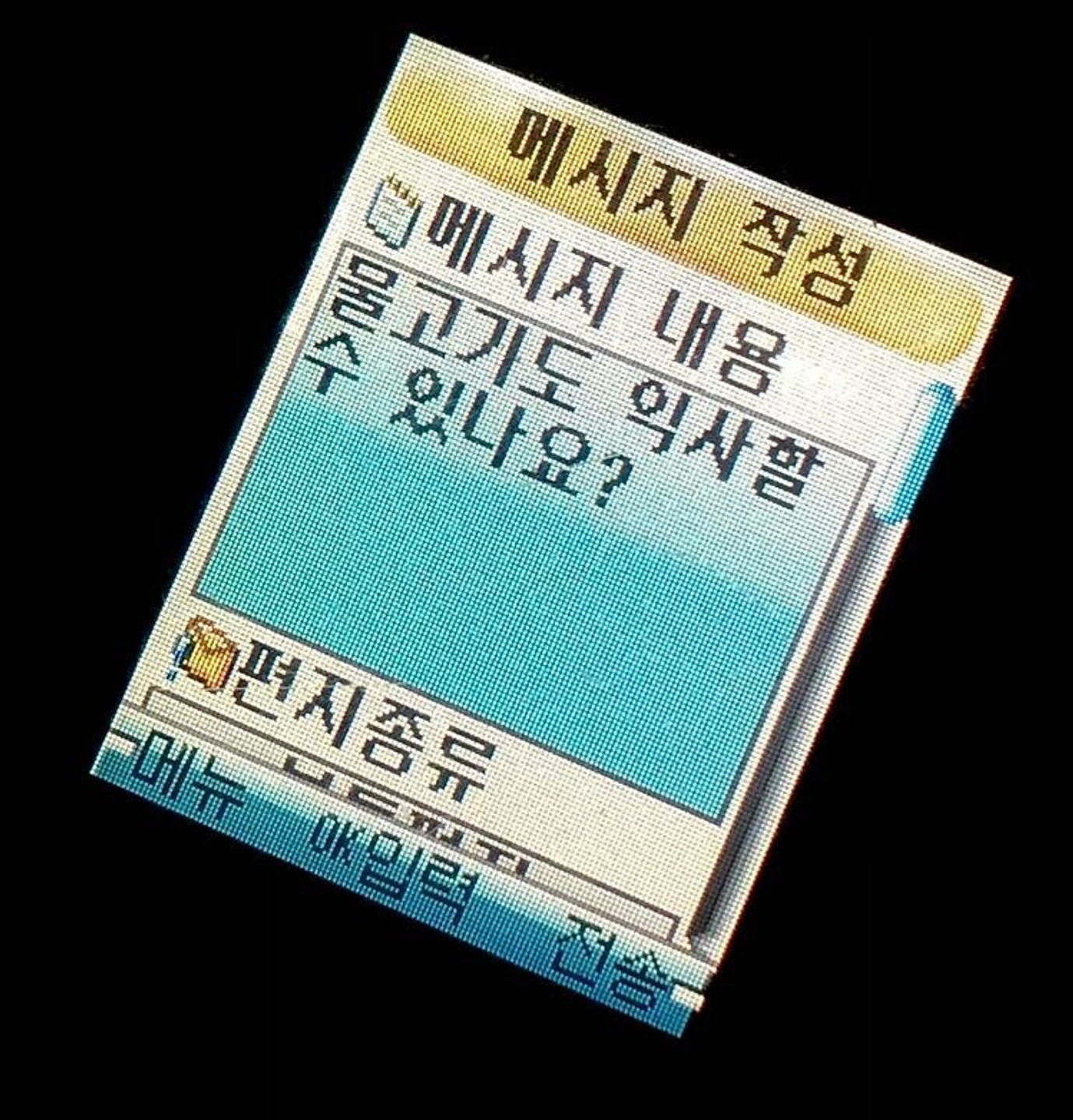
스카이 슬라이드 폰인데 너무 궁금해 남겨봐요... +) 둥근모꼴, 네오둥근모, 디테일 다 조금씩 달라요!!
기본체이면 아마도 PC 통신에서 쓰였던 둥근모 계열이 맞을거예요. 모바일용으로 따로 제작이 들어간거 같고요. 광수체, 무소체의 경우에도 이름은 같지만 디테일이 좀 달라요. 이 시절에는 비트맵 폰트라서 한 칸 안에 하나의 글자를 모두 도트로 찍어야하기 때문인데요. 가장 오래쓰였던 광수체를 예로 들자면 저해상도용으로 쓰인 광수체, QCIF 해상도에서 쓰인 광수체, QVGA 해상도에서 쓰는 광수체 등이 있어요. SKY폰에 무소체가 잠깐 사라지긴 했었지만, 무소체 또한 저해상도 무소체 및 QVGA 해상도용 무소체도 세로로 긴 특징만 표현했어요. 획의 꺾이는 부분은 거의 표현하지 않고 생략되었다고 보시면 돼요. 나중에 벡터폰트로 넘어가면서 PC에서 보는 폰트의 모양과 거의 똑같아졌어요.